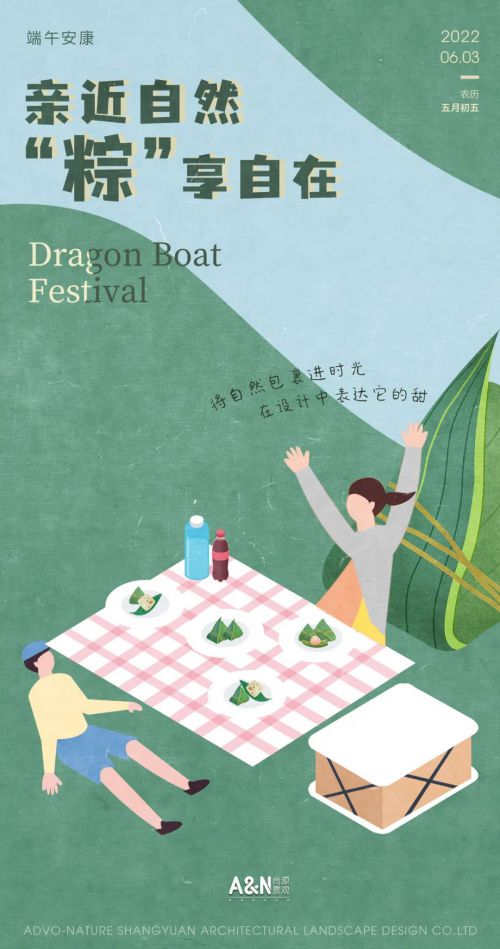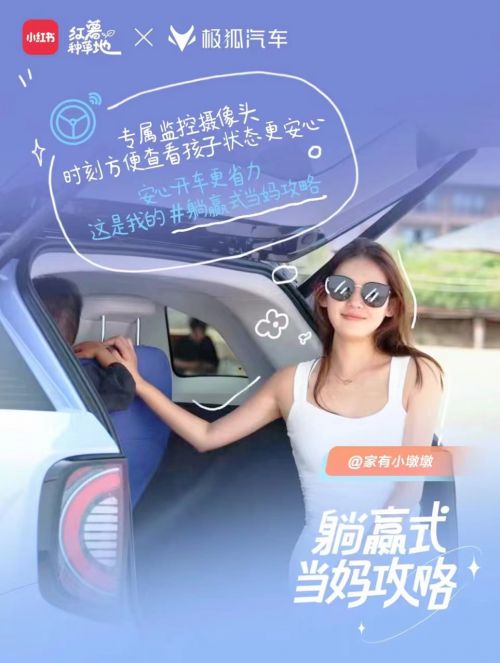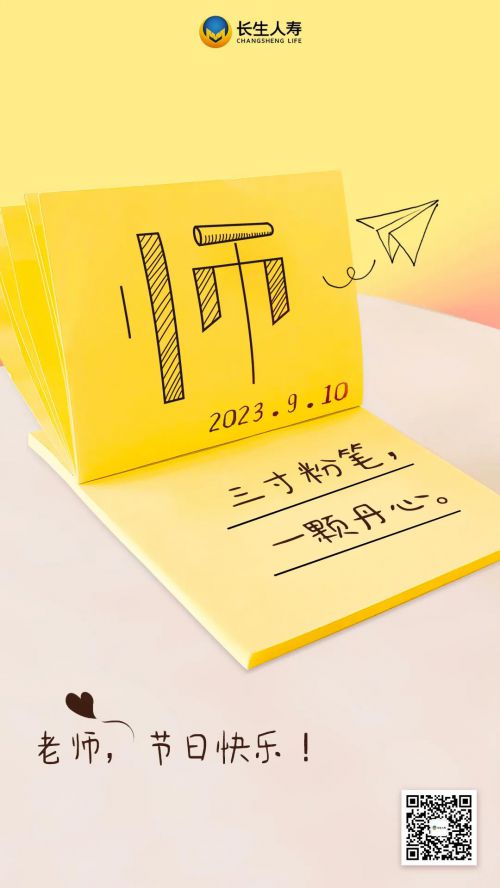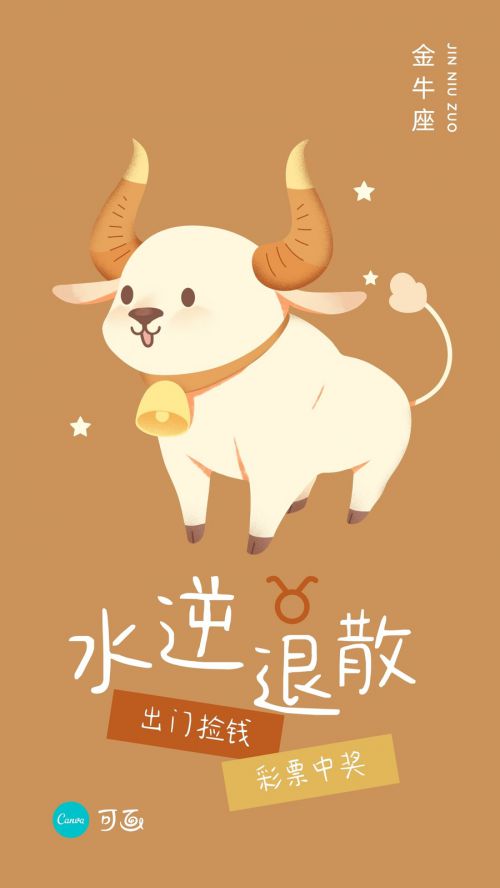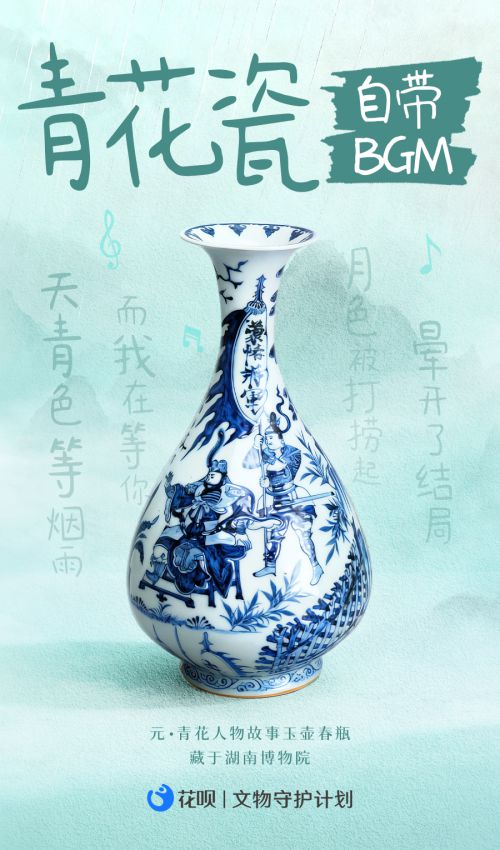
点字浅夏体
点字浅夏体是一款充满手写温度的卡通手写风字体,以活泼灵动的字形设计传递夏日般的轻松趣味。作为手写体家族中的一员,字体整体字形方正有度,重心居中平稳,中宫松紧适中,既保留了手写的随性笔触,又不失结构的工整协调。笔型设计尤为亮眼,圆角勾勒的笔画搭配圆头收尾,让每个字符都像被阳光吻过的气泡,轻盈又可爱;笔画间巧妙断开的连接方式,打破了传统书写的连贯感,反而增添几分跳跃的韵律,尽显“跳动”的活力。字体粗细纤细均匀,细而不弱的笔触带着手写的原生质感,落笔处的轻微不规则感,更让字体透出自然的俏皮气息。 作为点字库旗下免费商用字体,点字浅夏体覆盖常规字符集,适配简体中文场景,无论是社交媒体配图、儿童主题海报,还是文创手账、趣味标题设计,都能以其独特的手写风味点亮视觉,让创意表达自带夏日般的清新与灵动。